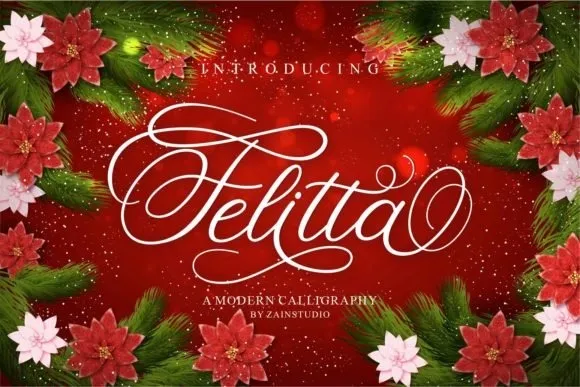
A ‘Felitta Font’ é uma elegante tipografia inspirada no estilo clássico, oferecendo um toque único para qualquer projeto de design. Com seu traço suave e linhas perfeitamente definidas, esta fonte proporciona um toque autêntico e realista que transforma a experiência do usuário em uma obra-prima visual. É especialmente perfeita para cartões de casamento, cards de agradecimento, citações e cartões de felicitações, fazendo-as se destacarem ao mesmo tempo que mantêm um estilo elegante e sofisticado. Além disso, o recurso de alternativas únicas da ‘Felitta Font’ permite criar ambientes de design personalizados e altamente detalhados, atraindo olhares curiosos sem esforço. É uma escolha perfeita para qualquer projeto que deseje dar um toque único e autêntico a suas criações gráficas.